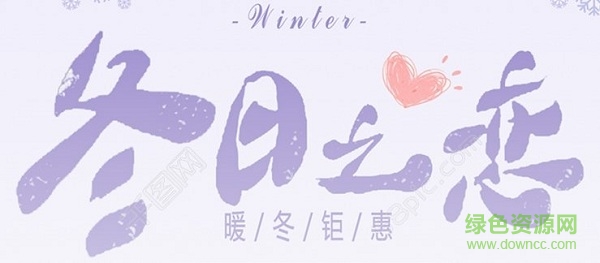
漢儀冬日之戀字體
漢儀冬日之戀是一款十分大氣美觀的漢儀字體,給用戶帶來美妙雪景的怡然體驗,讓你有著極佳的視覺體驗,給設(shè)計別出心裁的創(chuàng)意效果,綠色資源網(wǎng)獨家推薦!
冬日之戀字體特色
漫步林間,寒風(fēng)飄雪落在指尖,那么涼,那么輕,似戀人的手撫摸我的心頭,牽扯我的思念。凝心遠望,期待這一季的冬日之戀。
漢儀冬日之戀字體帶給大家無盡的想象與追憶,讓人在溫暖的冬陽中感受不一樣的愛戀,字跡柔和而飄逸,讓你的文字更加溫柔繾綣人心,給你的平面設(shè)計、藝術(shù)創(chuàng)作更多美感!